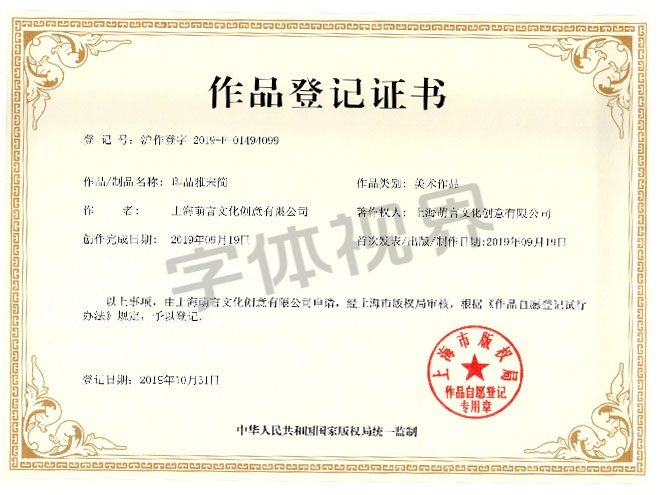
字体简介:在做印品雅宋简这款字体设计之前,设计师翻阅了许多关于宋体的资料,从古至今宋体多用于各类文章的正文排版,自然少不了正式感,那么,如何在不减少正式感的情况下又能增添一些个性的小细节进去呢?设计师开始了自己的思考,于是把将宋体原有的尖端,都改成了圆润平滑的角,变成这款字体的装饰部分,让整款字体看起来既不缺少正式感又能增添个性的感觉。此款字体分三种字重,分别是印品雅宋简 中黑;印品雅宋简 粗体;印品雅宋简 粗斜
字体名称:印品雅宋简
所属分类: 宋体